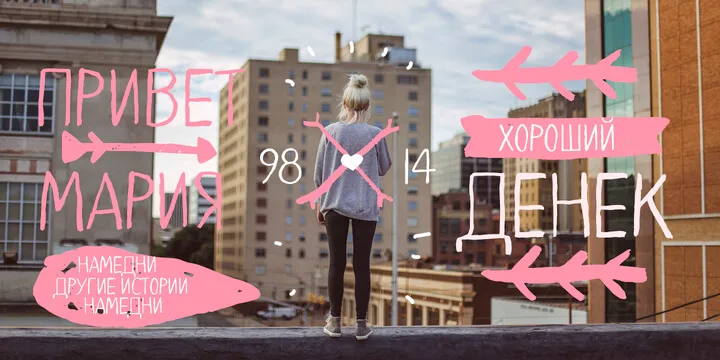
Сумасшедшие шрифты 2. Кириллица
Данный продукт представляет собой набор графических шрифтов, выполненных в веселом и эксцентричном стиле. Пакет включает в себя гарнитуры, поддерживающие как латинскую, так и кириллическую раскладки, что делает их универсальным инструментом для оформления различных визуальных проектов.
Основной функционал
- Поддержка двух алфавитов: латиницы и кириллицы.
- Уникальный визуальный стиль: шрифты характеризуются как «веселые» и «сумасшедшие», что позволяет использовать их для создания акцентных надписей, заголовков и креативного дизайна.